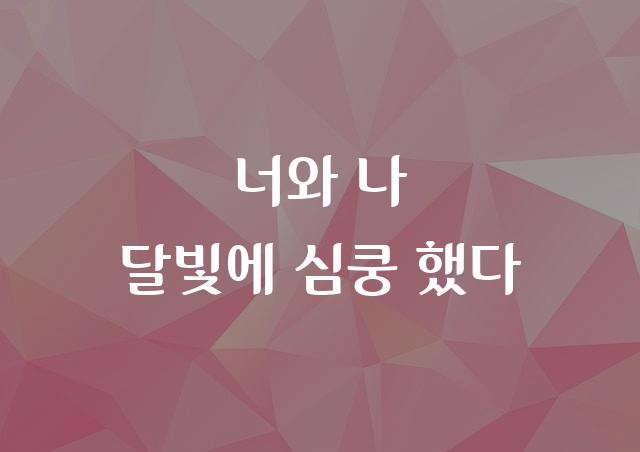
달서달링체는 달서구청에서 제작한 장식체로서, 제목용으로 사용하기 적합한 둥근 고딕 폰트입니다. 부드러운 곡선과 편안한 가독성이 특징이며, 따뜻한 감성을 전달합니다.
달서달링체은(는)
별모양/패턴, 길고/크고, 기본 고딕, 복실복실, 부드러움, 감성적인, 장식 스타일, 둥근 스타일 계열의 생김새를 가지고 있으며
포스터, 소셜 미디어, 어린이 책 등에서 자주 활용되며, 효과적인 메시지 전달에 적합합니다.
이 폰트는 크리에이티브, 문화/예술, 엔터테인먼트 분야에 잘 어울리며,
재미있는, 창의적인, 귀여운 느낌을 담고 있는 것이 특징입니다.